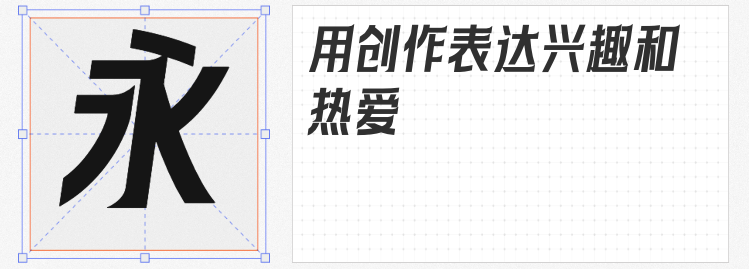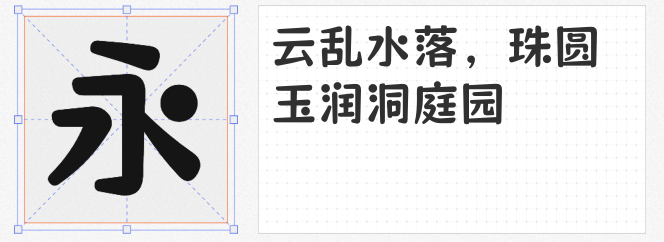
在设计的奇妙世界里,字体是传递情感与风格的关键元素。今天就为大家推荐四款免费商用且风格俏皮、个性十足的字体,让你的设计瞬间脱颖而出。
快看世界体由快看KKDC精心打造,以漫画对话框元素为灵感源泉,深度融入快看ACGN文化,尽显年轻潮流与大胆态度。其字体末端尖角设计独特,中宫外扩、字面瘦长且倾斜8度,这种独特造型赋予了字体强烈的动态感与时尚气息。无论是快看品牌营销、漫展活动,还是内部企业文化宣传、客户端界面,快看世界体都能完美适配,成为传递年轻活力的视觉符号。
猫啃珠圆体宛如一位萌趣十足的欢乐使者,笔画圆润饱满,风格动感活泼、俏皮可爱。它仿佛自带魔力,能瞬间为儿童、母婴产品以及萌系动画等场景增添天真可爱、无拘无束的活力。这款字体不仅适合作为标题字体吸引眼球,用于正文排版时,也能营造出萌萌的氛围,让读者沉浸在温馨欢乐的阅读体验中。
Aa厚底黑在设计上独具匠心,选用窄长字形,展现出强烈的现代感。同时,搭配弧度较大的曲线和特别厚的底,让字体充满了活泼灵动的气息。这种独特的设计使得Aa厚底黑在众多字体中脱颖而出,无论是用于海报设计、广告宣传,还是包装设计等领域,都能为作品注入一份别样的活力。
字帮玩酷体正如其名,字形风趣幽默,笔画多元且错落有致,风格轻松玩趣。它收录了GBK编码共20923个文字及987个符号,能够满足各种复杂的使用场景。无论是创意海报、趣味插画,还是社交媒体宣传,字帮玩酷体都能以其独特的风格为设计增添一份趣味与创意。
这四款免费商用字体各具特色,无论是追求潮流、萌趣、现代还是玩趣,都能满足你的设计需求。赶快将它们运用到你的作品中,开启一场充满创意与活力的设计之旅吧!